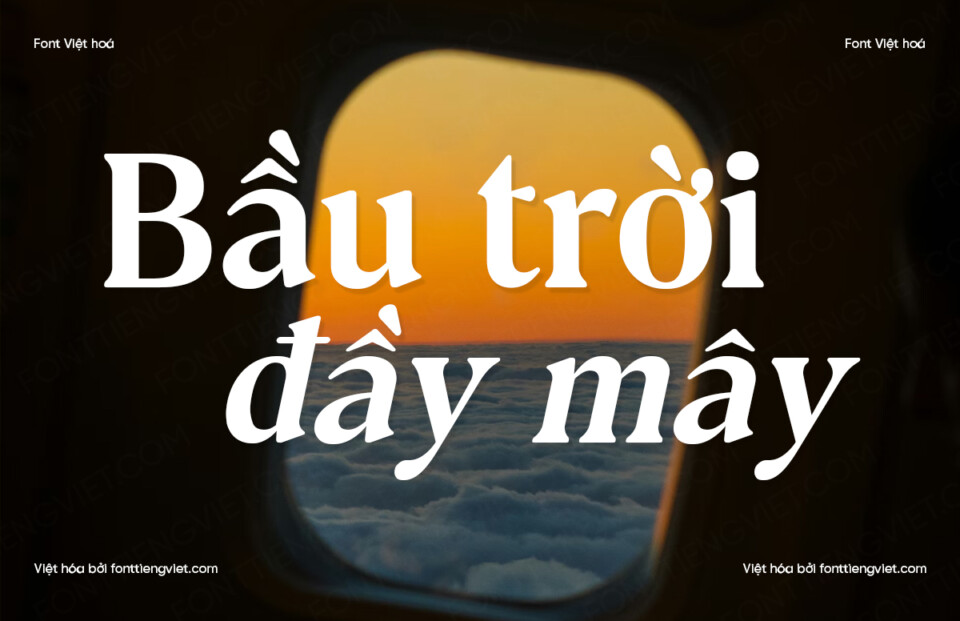
2 Font Việt hóa 1FTV VIP Exclusive Editorial
Tải trọn bộ 2 Font Việt hóa 1FTV VIP Exclusive Editorial thiết kế chuyên nghiệp
Giới thiệu về bộ 2 Font Việt hóa 1FTV VIP Exclusive Editorial
Trong thế giới thiết kế đồ họa hiện đại, việc lựa chọn Font Miễn Phí chất lượng đóng vai trò quyết định đến tính thẩm mỹ và sự chuyên nghiệp của sản phẩm. Bộ 2 Font Việt hóa 1FTV VIP Exclusive Editorial là một sự lựa chọn tinh tế dành riêng cho những ai đang tìm kiếm phong cách biên tập (editorial) sang trọng và đẳng cấp. Được tuyển chọn kỹ lưỡng, bộ font này không chỉ mang lại vẻ đẹp cổ điển mà còn pha lẫn hơi thở đương đại, giúp các nhà thiết kế dễ dàng truyền tải thông điệp một cách ấn tượng nhất.
Tại sao nên sở hữu bộ font Exclusive Editorial?
Sự đặc biệt của bộ 2 Font Việt hóa 1FTV VIP Exclusive Editorial nằm ở cấu trúc đường nét thanh mảnh nhưng vô cùng chắc chắn. Kiểu chữ này được tối ưu hóa cho các tiêu đề tạp chí, bìa sách hoặc các chiến dịch quảng cáo cao cấp. Việc Việt hóa hoàn chỉnh giúp các bạn học sinh, sinh viên và nhà thiết kế tại Việt Nam không còn lo lắng về lỗi hiển thị dấu tiếng Việt, đảm bảo sự mượt mà trong mọi bố cục chữ viết.
Đặc điểm nổi bật của 2 Font Việt hóa 1FTV VIP Exclusive Editorial
Bộ font này bao gồm hai phong cách đối lập nhưng bổ trợ hoàn hảo cho nhau, tạo nên sự cân bằng thị giác tuyệt vời. Một font mang thiên hướng Serif (có chân) truyền thống để khẳng định uy tín, trong khi font còn lại mang nét hiện đại để tạo điểm nhấn phá cách. Khi kết hợp 2 Font Việt hóa 1FTV VIP Exclusive Editorial, bạn sẽ tạo ra được những phân cấp nội dung rõ ràng, giúp người đọc dễ dàng tiếp nhận thông tin mà không cảm thấy nhàm chán.
Ứng dụng trong giáo dục và thiết kế học đường
Đối với môi trường học đường, bộ font này là công cụ hỗ trợ đắc lực cho các bài thuyết trình, báo cáo nghiên cứu hoặc làm tập san trường học. Sự trang trọng của 2 Font Việt hóa 1FTV VIP Exclusive Editorial giúp các tài liệu giáo dục trở nên chỉn chu hơn, rèn luyện tư duy thẩm mỹ cho học sinh ngay từ khi ngồi trên ghế nhà trường. Thay vì sử dụng những phông chữ mặc định đơn điệu, việc thay đổi sang bộ font chuyên dụng này sẽ nâng tầm giá trị cho mọi dự án sáng tạo cá nhân.
Để phát huy tối đa vẻ đẹp của 2 Font Việt hóa 1FTV VIP Exclusive Editorial, người dùng nên chú trọng đến khoảng cách giữa các chữ cái (kerning) và dòng (leading). Trong các phần mềm như Photoshop hay Illustrator, bạn có thể tinh chỉnh các thông số này để tạo ra những khối văn bản nghệ thuật. Lưu ý rằng bộ font này tỏa sáng nhất khi được dùng làm tiêu đề lớn hoặc các trích dẫn quan trọng, nơi mà các chi tiết thiết kế của chữ được phô diễn rõ nét nhất.
Tổng kết về bộ 2 Font Việt hóa 1FTV VIP Exclusive Editorial